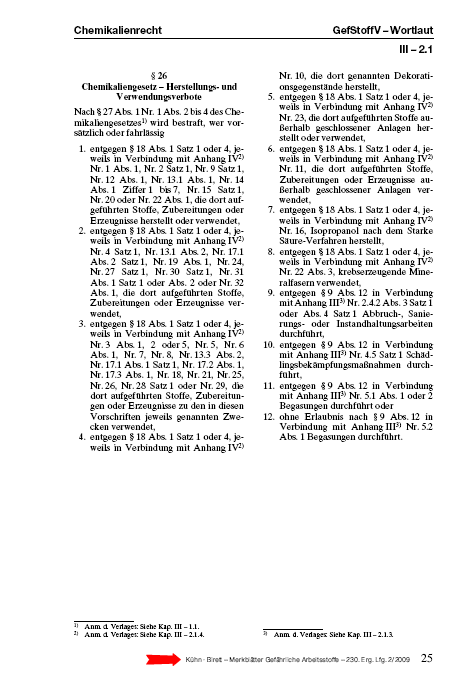
Wie heisst das richtig? - Text neben der Seitenzahl
Bei uns im Verlag gabs verschiedene versionen, wie der Text neben der Seitenzahl heisst, bei uns enthält das, wie Werktitel, Autor und Erscheinungsdatum.
Ist also eigentlich ein toter Kolumnentitel, aber eben unten an der Seite.
Es kursierten bisher die Bezeichnungen Norm, wohl abgeleitet von der Bogennorm, wird aber jetzt ersetzt durch den Begriff Kustode.
Kann mich da jemand aufklären?
Meinst Du diese Bogenbezeichnung, die man in älteren Büchern noch findet?
Der Text den Du in der untenstehenden Beispielabbildung oben neben der Seitenzahl siehst, ist der lebende Kolumnentitel (hier: Welche Auffassung …). Das, was Du hier unten am Fuß der Seite siehst, ist die Norm bzw. Signatur. Während der Kolumnentitel auf jeder Textseite steht, kommt die Norm nur auf der ersten und dritten Seite eines jeden Druckbogens vor. Sie enthält die Bogennummer (hier: 3) und möglicherweise den Kurztitel (hier: Stalin, Werke …). Die Norm ist in Prime (auf der ersten Bogenseite) und Sekunde (auf der dritten Bogenseite) geteilt. Bei der Sekunde steht hinter der Bogennummer ein Stern, der Kurztitel wird hier meist weggelassen. Jede Druckform (Schön- und Widerdruck) hat also je eine Signatur. Da der dritte Bogen hier bei Seite 33 beginnt, kann man sehen, daß dieses Buch in Bogen je 16 Seiten gedruckt wurde. Die Bogennorm war wichtig als Orientierungshilfe für den Schriftsetzer, den Drucker und den Buchbinder, um die Bogen vom Blei bis zum Buchblock jederzeit auf den ersten Blick auseinanderhalten zu können. So standen z. B. die Bleiseiten immer so auf dem Satzbrett, daß Prime und Sekunde nach vorn zeigten, so daß das schwere Satzbrett kaum aus dem Satzregal herausgezogen werden mußte, um den richtigen Bogen zu identifizieren. Da die Satzbretter mehrmals durch die Setzerei transportiert wurden (z. B. bei jedem Korrekturgang zur Abziehpresse und wieder zurück in die Gasse des jeweiligen Setzers) kann man sich schon hier die Wichtigkeit der Signatur vorstellen.
Für aufwendigere Bücher wurde die Bogennorm außerhalb des Beschnitts gestellt, beim endgültigen Beschnitt des Buchblockes wurde sie mit weggeschnitten. In heutigen Büchern findet man kaum noch sichtbare Bogensignaturen; ob dies daran liegt, daß man sie heute grundsätzlich außerhalb des Beschnitts stellt oder ob sich die Signatur aufgrund der Automatisierung völlig überlebt hat, kann ich nicht sagen.
Das Wort Kustode hat mehrere Bedeutungen, jedenfalls kann ausgeschlossen werden, daß Du in einem heute gedruckten Buch eine Kustode findest. Zu meiner Zeit war die Kustode eine persönliche Signatur des (Maschinen-)Setzers, die zu Abrechnungs- und Kontrollzwecken diente und beim Umbruch aus dem Produktionsablauf in Richtung Altblei verschwand.
Der Text neben der Seitenzahl kann also eigentlich nur der Kolumnentitel sein, weil die Signatur nie neben der Seitenzahl stehen sollte (auch dann nicht, wenn die Seitenzahl am Fuß der Seite steht), sondern immer deutlich nach unten abgesetzt.
O.k. dass Kustode ein eher veralteter Begriff ist, habe ich schon vermutet :D
Im Gegensatz zu der beschriebenen Bogennorm, befindet sich das bei uns auf jeder Seite, ist alelrdings auch kein echtes Buch, sondern ein Loseblattwerk.
hier mal eine Beispielseite:
muster-seite4x9a.png
es geht und den Text neben dem Pfeil. Das Wort Kolumnentitel verbinde ich eben immer mit oben, und da haben wir ja auch einen :?
Stimmt, Kolumnentitel ist das, was Ihr da oben habt. Das Problem rührt daher, daß die Seite halt etwas unorthodox aufgebaut ist; dieses Etwas, das Ihr da unten stehen habt, kommt in keiner DIN vor und fällt deshalb auch durch das Raster der Bezeichnungen üblicher Seitenelemente. Also kann man das im Prinzip auch nennen, wie man will, Ihr könnt »Meyer« dazu sagen, »Hugo«, »Kennzeichnungsbereich zur Verbesserung der Spontanidentifikation eines Einzelelements innerhalb einer Printmedienkollektion« oder »Dingsbums«, es wird Euch niemand dafür steinigen. Am ehesten ist das natürlich eine Art von Signatur, aber eben nicht die Signatur.
Der Seitenaufbau ist übrigens ohnehin sehr überdenkenswert. Das könnte man sicher mit ein paar Handgriffen übersichtlicher und professioneller machen.